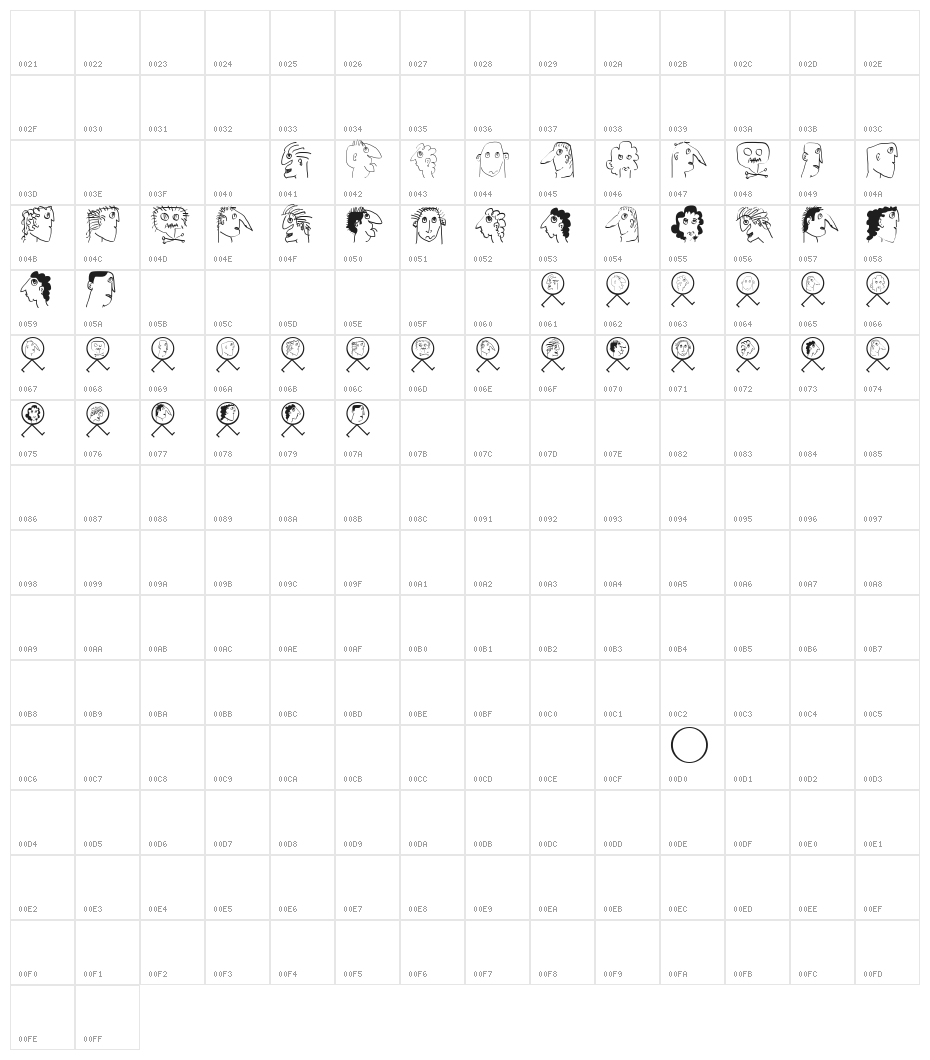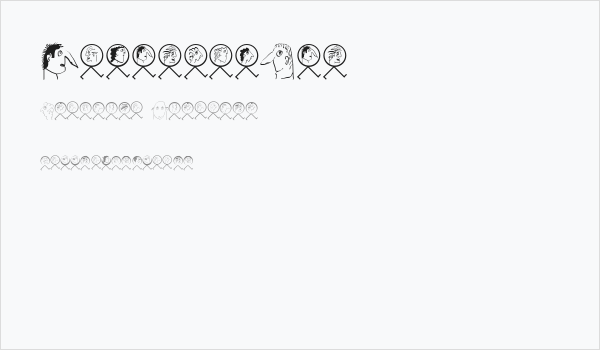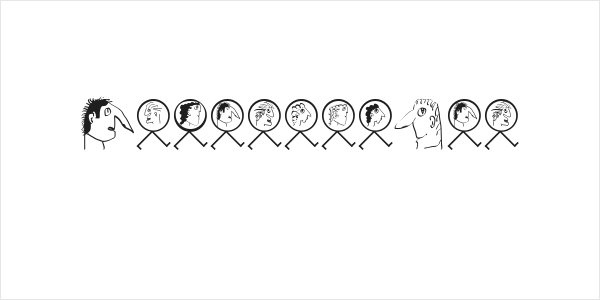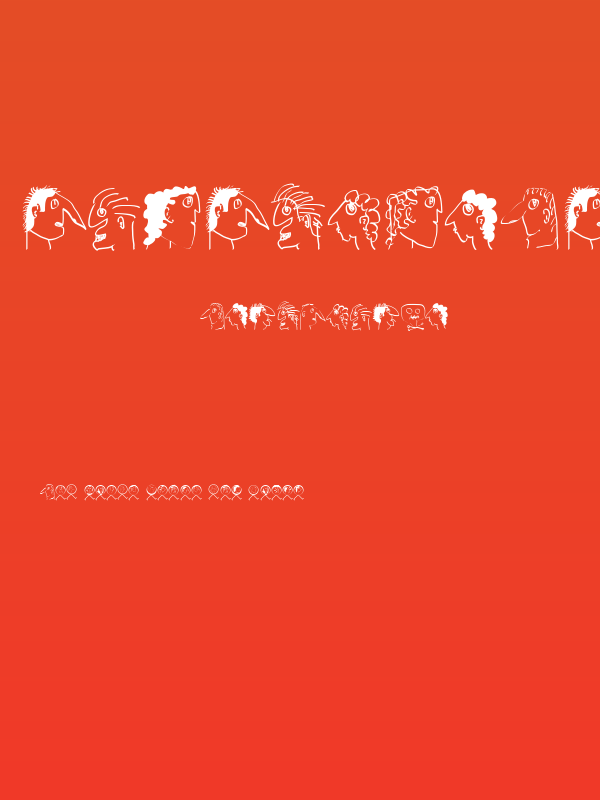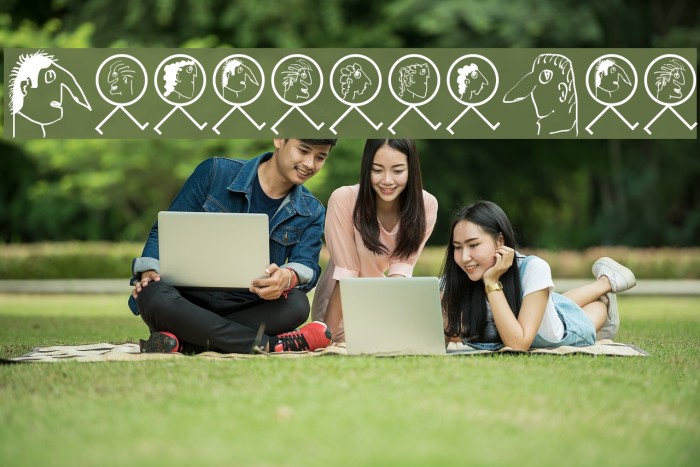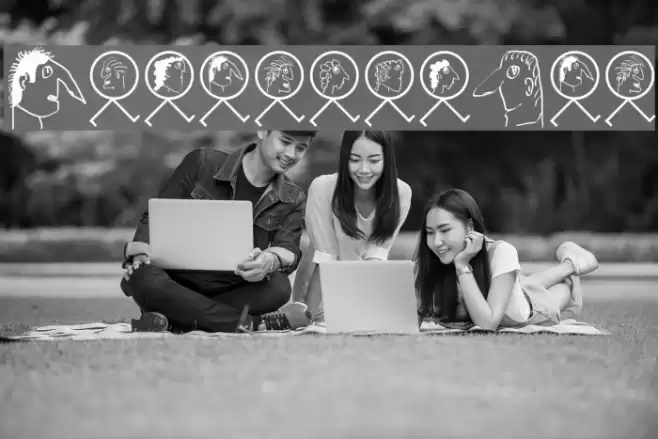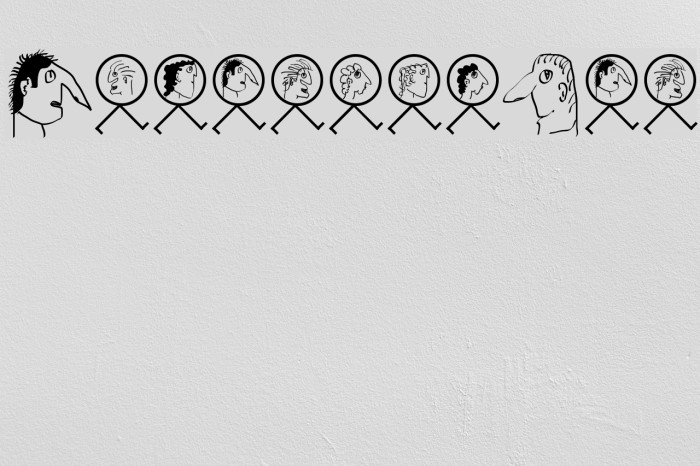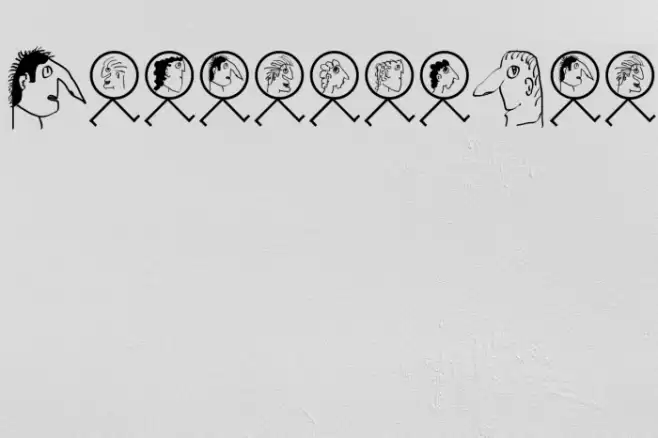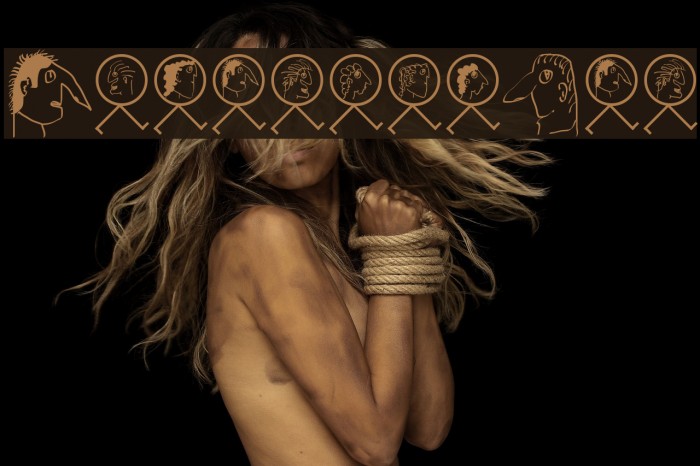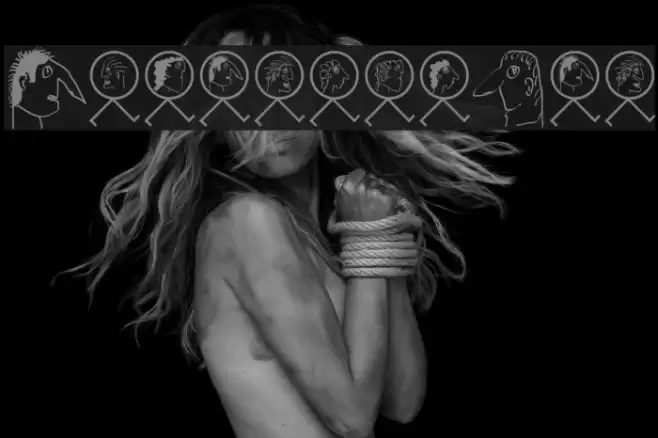
WaxworksTwo Font
| Estilo geral | Artistic, Whimsical |
| Caso de uso | Illustrations, Artistic projects |
| Projetos propostos | Ideal for creative projects such as children's books, comic strips, or playful branding materials where unique character illustrations are needed. |